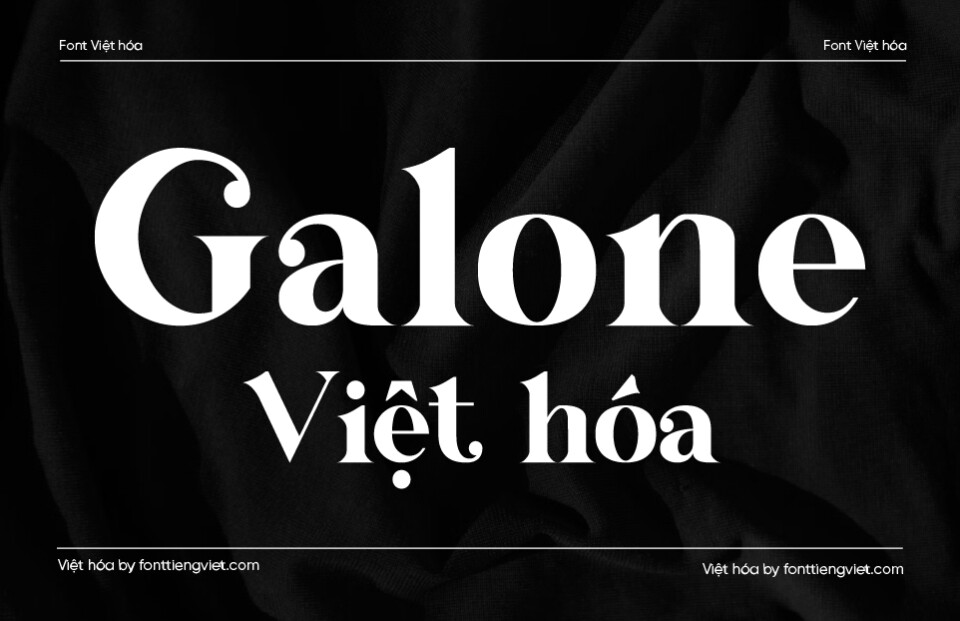
Font Việt hóa 1FTV VIP Galone
Giới thiệu về bộ Font Việt hóa 1FTV VIP Galone
Trong thế giới thiết kế đồ họa hiện đại, việc lựa chọn một bộ Font Miễn Phí chất lượng luôn là ưu tiên hàng đầu của các nhà sáng tạo. Font Việt hóa 1FTV VIP Galone nổi lên như một hiện tượng nhờ sự kết hợp hoàn hảo giữa nét cổ điển sang trọng và hơi thở đương đại đầy tinh tế. Đây là bộ phông chữ thuộc phong cách Serif (có chân) nhưng được tinh chỉnh để giữ được sự thanh thoát, giúp các văn bản tiếng Việt trở nên chuyên nghiệp và dễ đọc hơn bao giờ hết. Với phiên bản Việt hóa chỉn chu, người dùng không còn phải lo lắng về lỗi hiển thị dấu câu hay khoảng cách chữ không đều, giúp quy trình làm việc trở nên mượt mà và hiệu quả.
Những đặc điểm nổi bật của Font Việt hóa 1FTV VIP Galone
Thiết kế thanh lịch và đẳng cấp
Font Việt hóa 1FTV VIP Galone sở hữu những đường nét mảnh mai nhưng vô cùng sắc sảo. Các nét thanh và nét đậm được phối hợp nhịp nhàng, tạo nên một cấu trúc chữ vững chãi nhưng không kém phần mềm mại. Chính sự cân bằng này đã giúp bộ font trở thành lựa chọn lý tưởng cho các ấn phẩm yêu cầu tính thẩm mỹ cao như tạp chí thời trang, thiệp mời cao cấp hay bìa sách nghệ thuật. Khi sử dụng Galone, dự án của bạn sẽ ngay lập tức toát lên vẻ ngoài của một thương hiệu cao cấp và có chiều sâu văn hóa.
Khả năng ứng dụng đa dạng trong thực tế
Không chỉ giới hạn trong lĩnh vực in ấn, Font Việt hóa 1FTV VIP Galone còn phát huy tối đa sức mạnh trong các thiết kế kỹ thuật số. Bạn có thể sử dụng bộ phông này để tạo nên những tiêu đề website ấn tượng, các bài đăng trên mạng xã hội thu hút thị giác hoặc thậm chí là trong các bài thuyết trình chuyên sâu tại trường học. Đối với các bạn học sinh và giáo viên, việc sử dụng một bộ font chữ sạch sẽ, rõ ràng như Galone sẽ giúp bài giảng và bài tập trở nên sinh động, dễ tiếp thu và thể hiện sự tôn trọng đối với người xem thông qua sự chỉn chu trong trình bày.
Cách tối ưu hóa Font Việt hóa 1FTV VIP Galone trong thiết kế
Lựa chọn màu sắc và bố cục phù hợp
Để Font Việt hóa 1FTV VIP Galone thực sự tỏa sáng, các nhà thiết kế nên kết hợp chúng với những gam màu trung tính như đen, trắng, vàng đồng hoặc xanh đen. Việc tạo ra những khoảng trắng hợp lý xung quanh các khối văn bản sẽ giúp chữ Galone có không gian để “thở”, từ đó làm nổi bật lên những đường cong tinh tế của từng ký tự. Ngoài ra, việc kết hợp Galone với một bộ font Sans-serif đơn giản cho phần nội dung chi tiết sẽ tạo nên một cấu trúc phân cấp thị giác hoàn hảo, giúp người đọc dễ dàng theo dõi thông tin quan trọng nhất.
Bộ Font Việt hóa 1FTV VIP Galone đã được tối ưu mã hóa chuẩn Unicode, tương thích tốt với các bộ gõ tiếng Việt phổ biến hiện nay. Khi cài đặt vào hệ thống, bạn chỉ cần lựa chọn đúng bảng mã để tận hưởng vẻ đẹp của từng dấu huyền, dấu sắc được đặt vị trí chuẩn xác. Sự tỉ mỉ trong khâu Việt hóa đảm bảo rằng dù bạn viết những đoạn văn dài hay các tiêu đề ngắn, vẻ đẹp tổng thể của ngôn ngữ Việt vẫn luôn được tôn vinh một cách trọn vẹn và trang trọng nhất.
Tổng kết về bộ Font Việt hóa 1FTV VIP Galone